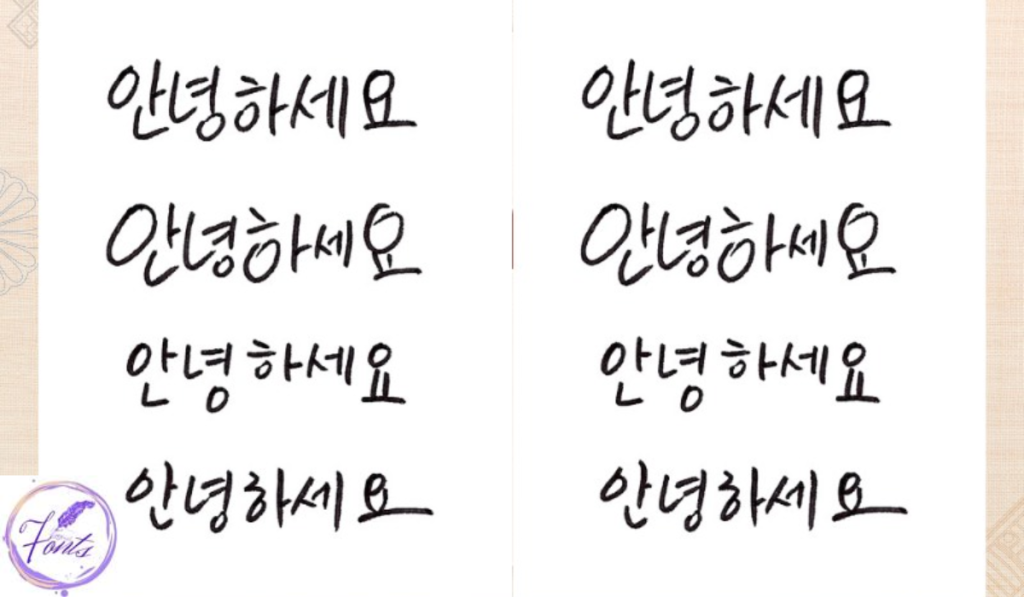
Font chữ Hàn Quốc viết tay
Ngôn ngữ: Hàn Quốc
Bộ Font: Đa dạng
Phân loại: Viết tay, cá tính
Kiểu chữ: Không chân
Độ dày: Thin, Regular
Nếu bạn đang tìm kiếm một phong cách chữ độc đáo và tràn đầy cảm xúc, font chữ hàn quốc viết tay là sự lựa chọn hoàn hảo. Được thiết kế mô phỏng theo nét chữ thật của người viết, bộ font này mang lại cảm giác chân thực và gần gũi. Dù là để thêm vào thiệp mời, poster hay bất kỳ tài liệu nào khác, font chữ hàn này sẽ làm cho sản phẩm của bạn trở nên nổi bật và ấn tượng, thể hiện được sự tinh tế và đầy tính nghệ thuật.
Đánh giá font chữ hàn quốc viết tay
Font chữ hàn quốc viết tay nhận được rất nhiều đánh giá tích cực từ cộng đồng thiết kế bởi sự linh hoạt và dễ sử dụng của nó. Với đa dạng các kiểu chữ, từ nhẹ nhàng đến mạnh mẽ, font này thực sự phù hợp với mọi ngữ cảnh, từ thương mại đến cá nhân. Font chữ hàn không chỉ giúp các thiết kế của bạn trở nên sinh động hơn mà còn mang đến một cách thể hiện cảm xúc độc đáo, khiến mỗi tác phẩm trở nên có hồn hơn.